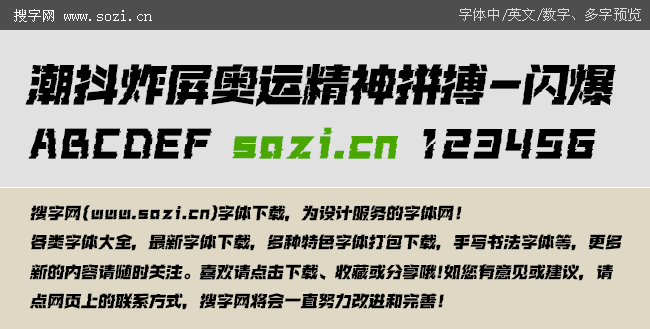
潮抖炸屏奧運精神拼搏-閃爆
搜字網給大家提供一款潮抖炸屏奧運精神拼搏-閃爆中文字體下載,潮抖炸屏奧運精神拼搏-閃爆是一款創(chuàng)意藝術字體,字體在奧運系列字形基礎上進行創(chuàng)新,糅合電音節(jié)奏、潮流風尚,賦予字體抖動切割的動態(tài)效果。適合應用于藝術設計、平面宣傳設計、網頁設計、海報設計等應用。